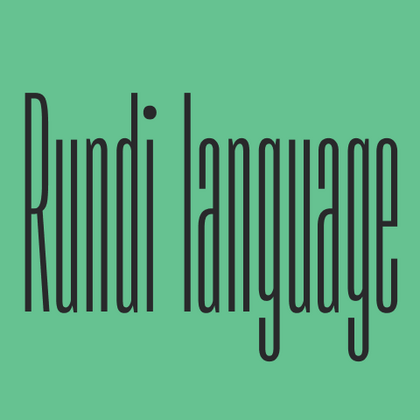
Подборка Рунди шрифтов
В коллекции TypeType представлены шрифты на языке Рунди. Профессиональные шрифты с полной поддержкой языка рунди гарантируют корректное отображение всех лингвистических особенностей, включая специальные диакритические знаки и символы. Такие гарнитуры разработаны для образовательных материалов, официальной документации и медиа-контента на этом языке.
Выберите подходящий шрифт с поддержкой Рунди языка. Огромная коллекция шрифтовых семейств для любых целей и задач: набор больших текстовых массивов, оформление заголовков для веб-сайтов и печатных изданий, печать на текстиле и других материалах, оформление вывесок и афиш.
Каждый из представленных шрифтов содержит Рунди алфавит. Широкий выбор символов, знаков валют и пунктуации, шрифтовых начертаний и OpenType фич позволят применять один шрифт для разных проектов. Знаки расширенной латиницы, содержащие диакритические знаки, расширят возможности использования шрифта для разных стран.
Каждый шрифт безупречен с технической точки зрения. Многие шрифты из коллекции содержат вариативное начертание, с помощью которого можно создавать уникальное начертание для проекта.
TT Severs — это геометрический гротеск с ярко выраженными элементами внутренних скруглений. Отличительной особенностью TT Severs является необычная форма внутренних овалов, которая отсылает нас к стилю традиционной арабской письменности.
TT Turns — геометрический гротеск с акцентными круглыми знаками и выразительными нависающими элементами. Это универсальный шрифт, который лаконично выглядит и отлично читается в маленьком размере, при этом в крупных кеглях становится акцидентным и проявляет свой характер на максимум. Он энергичный, сильный и динамичный — особенно отчётливо это проявляется в наклонных начертаниях.
TT Jenevers стилистически относится к голландским антиквам нового стиля. В гарнитуре присутствуют характерные детали, свойственные голландским антиквам — это ассиметричная форма засечек или нерегулярный наклон овалов.
TT Regins — шотландская новостильная антиква с королевским характером. Яркий контраст и острые треугольные засечки придают этому шрифту строгий и властный нрав.
В TT Frantz можно найти небольшие отсылки в эстетике арт-деко, которые выражены в сильно заниженной или наоборот сильно завышенной талии у букв. Кроме того, в зависимости от положения ползунка регулировки оси, у некоторых букв изменяется закрытость апертуры.
TT Quaris — изысканная и современная ленточная антиква. Перед разработкой этой гарнитуры мы провели глубокое исследование архетипов ленточных антикв.
TT Ricordi Allegria — современная ленточная антиква, отличительные особенности которой, гиперболизированная разноширинность в пропорциях, контраст между штрихами, клиновидные окончания штрихов и отсутствие традиционных засечек.
TT Bakers — пластичная антиква с нежным и живым характером. Этот шрифт похож на свежую выпечку: он тёплый и мягкий, особенно в жирных начертаниях.
TT Supermolot Neue — технологичный модульный гротеск. Это мощный и динамичный шрифт с футуристическим настроением. «Сквадраченные» формы придают ему брутальности, при этом срезанные углы в отдельных элементах делают его пластичным и эргономичным.
TT Modernoir — акцидентный гротеск с разноширинными пропорциями. Плавные линии и изящные формы ар-нуво в этом шрифте сочетаются с ритмичностью и импровизационной свободой джаза.
TT Moons — узкая и контрастная антиква. Данное шрифтовое семейство очень элегантно работает в классических темах дизайна. TT Moons по стилистике относится к глиптальным новостильным шрифтам. Идеальная сфера использования TT Moons — это верстка журналов, книг и газет.
TT Neoris — лаконичный неогротеск с безграничными возможностями. Мы уделили особое внимание деталям, cделали наклонные начертания в кириллице визуально отличными от латиницы, соответствующими традиции кириллической каллиграфии.
TT Disruptors — дуктальный рукописный шрифт, созданный с помощью маркера. Его рисунок уникален: потёртости, неравномерная толщина штрихов и удлинённые выносные элементы придают ему живую, динамичную текстуру и ощущение рукотворности. Характер этого шрифта своенравный и эмоциональный, но при этом тёплый и душевный.
TT Gentlemens — динамичный рукописный шрифт, в котором серьёзность и чёткость письма сочетается с элегантностью и изысканностью. У него характер и стиль настоящего джентльмена: сдержанный и всегда уместный, но при этом уверенный и эффектный.